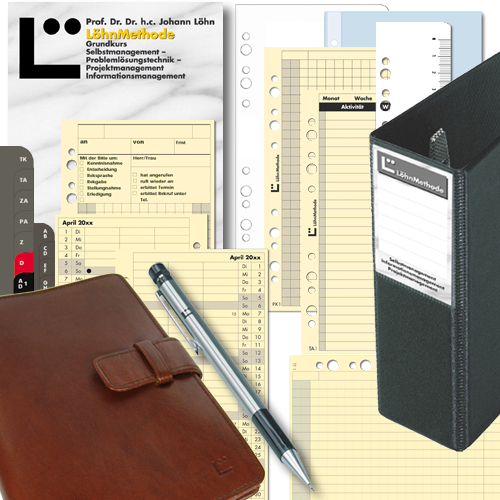
Suche schön gestalteten Terminkalender 2018
Die meisten sind typografisch ja nicht gerade Leckerbissen. Hat da jemand Empfehlungen?
hmmm ... zum Beispiel: coelho Kalender.
Die Firma coda KG in Waldkirch/Breisgau vertreibt das Kalendersystem von Prof. Löhn. Für mich nach wie vor haptisch und gestalterisch das Beste am Markt!
Grafisch sprechen mich die Kalenderseiten überhaupt nicht an. Unschöne Schriftmischungen, sehr dicke Linien und so weiter ... wirkt auf mich recht antiquiert.
...bist Du sicher, das wir von derselben Sache sprechen? Und hast Du einen aktuellen Planer vor Dir liegen?
Du meinst die Löhn-Methode? Die wirkt auch auf mich ebenfalls etwas antiquiert …
Ja Ihr Lieben! So ist das mit dem Thema "Wahrnehmung"! "Watt dem einen sin Uhl, iss dem annern sin Nachtigall..."